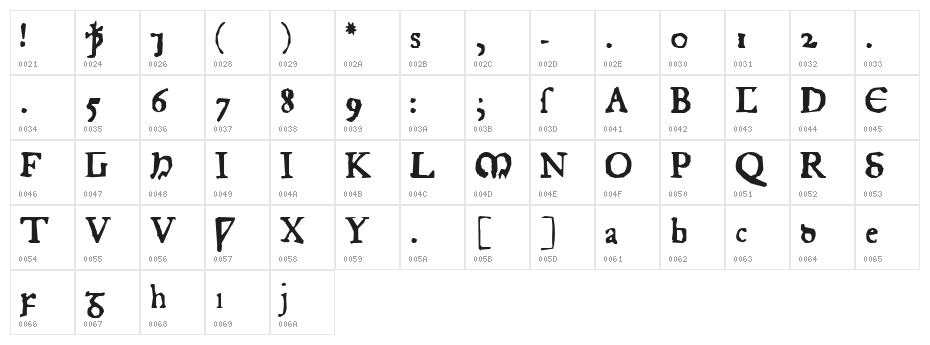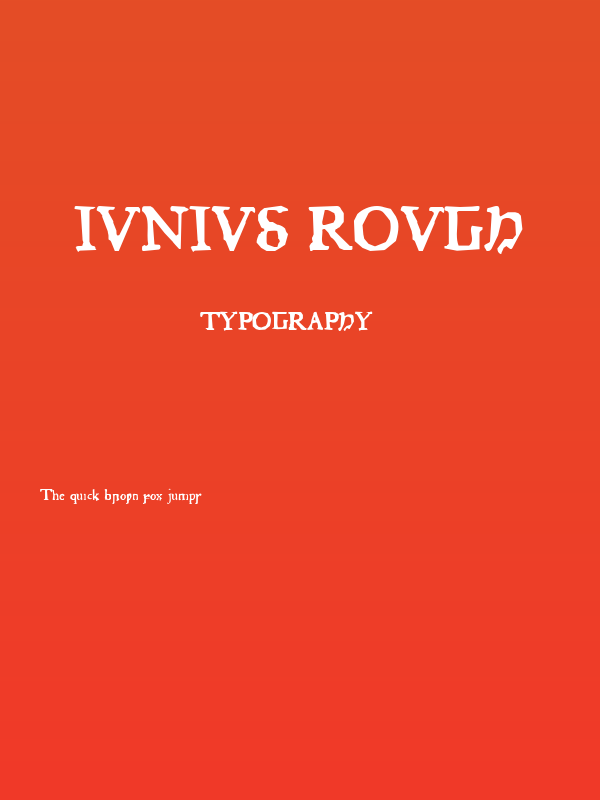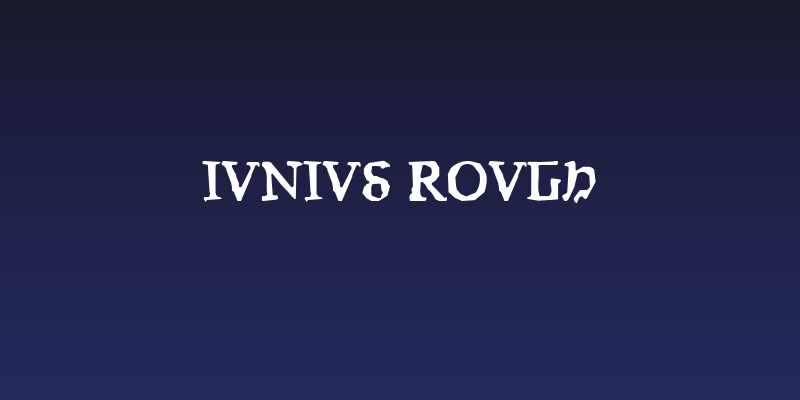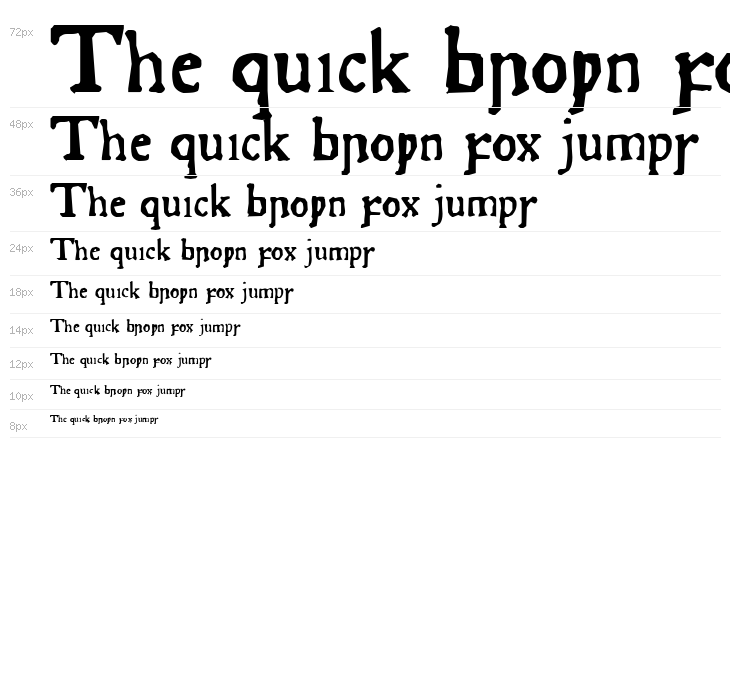
Junius Rough Font
| Gesamtstil | Vintage |
| Anwendungsfall | Logos, Headlines, Decorative text |
| Vorgeschlagene Projekte | Ideal for historical themed designs, fantasy book covers, medieval event invitations, and vintage posters. |